Fonts, dé guideline voor letters in je zakelijke huisstijl!
Letters zijn een belangrijk onderdeel bij drukwerk. Ze moeten niet te klein zijn, niet te groot en ook de kleur is essentieel voor de juiste weergave en leesbaarheid. Een Font geeft een gedetailleerde beschrijving van een lettertype – of beter gezegd – van de letterstijl en de lettergrootte. Het is dé guideline voor letters in je zakelijke huisstijl! Wat is het verschil tussen Font en lettertype? En hoe maak je een Font?
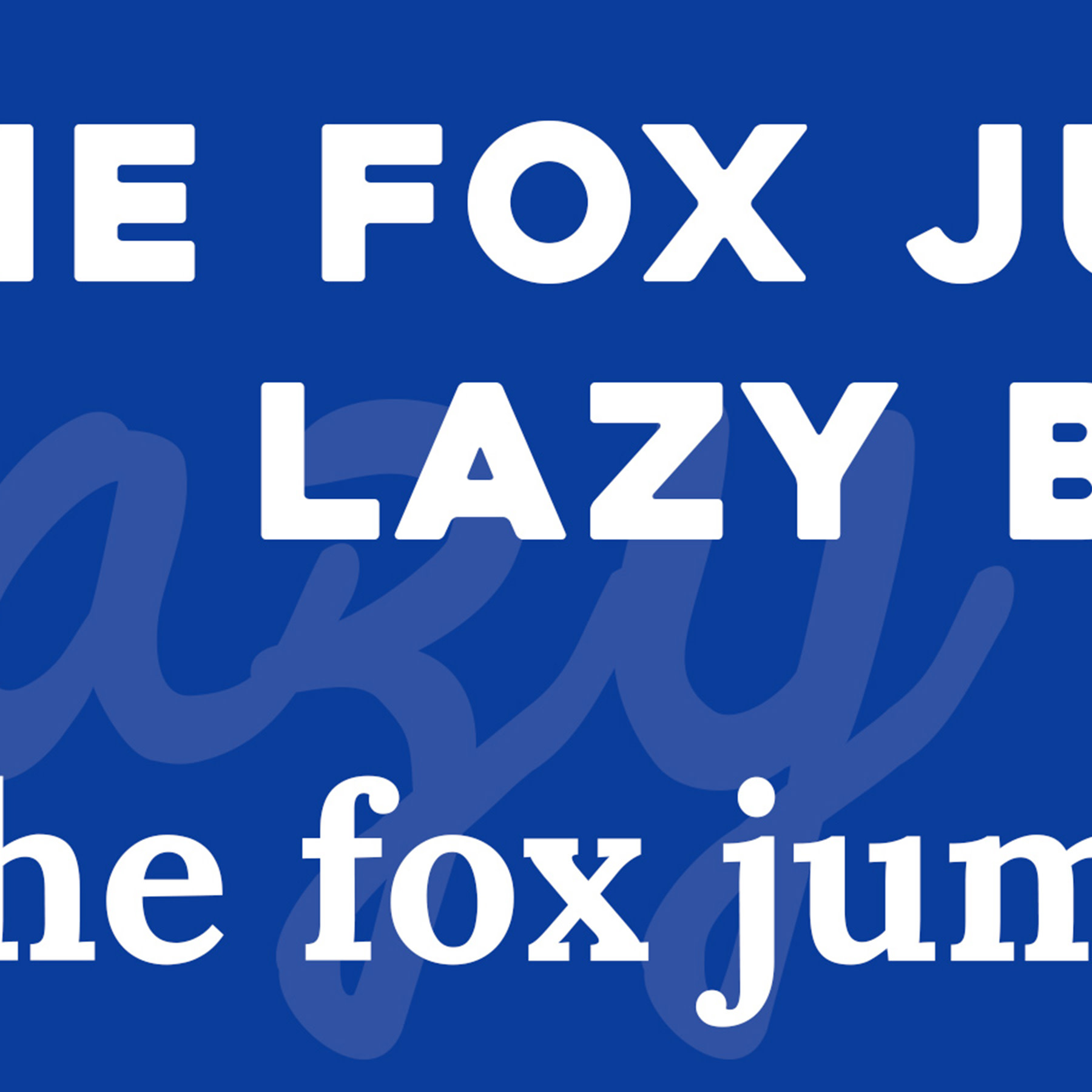
Het juiste lettertype kiezen voor je logo en huisstijl is belangrijk. Het draagt namelijk enorm bij aan de look & feel van je bedrijf. Welke indruk wil je in de eerste oogopslag maken? Moet het groots en uitbundig zijn? Of is het juist een bescheiden boodschap, verpakt in een fijne letterstijl? Veel bedrijven leggen de lettertypes die ze gebruiken vast in een huisstijlhandboek en voeren op die manier één lijn door in de Fonts op briefpapier, visitekaartjes, brochures, flyers, postermateriaal en ander drukwerk.
Binnen een zakelijke huisstijl wordt vaak één lettertype gehanteerd, maar wel meerdere Fonts. Dat komt omdat een lettertype - zoals de naam al zegt - alleen het lettersoort beschrijft, oftewel het type. Een Font is gedetailleerder. Veel mensen denken dat Font en lettertype hetzelfde is, ze worden vaak door elkaar gehaald. We hebben de verschillen voor je op een rij gezet.
Een lettertype is een set letters dezelfde stijl. Spreken we over een lettertype, dan hebben we het over het ontwerp van de letters. Bekende lettertypes zijn: Arial, Comic Sans, Times New Roman en Roboto. Een lettertype zegt niets over de grootte van de letters of over de stijl (dikgedrukt of cursief bijvoorbeeld).
Een Font geeft een complete beschrijving van de letters. In de ontwerpfase wordt door een vormgever vaak één of meerdere Fonts gemaakt, die in de gehele huisstijl van het bedrijf worden doorgevoerd. Een Font vertelt de gebruiker wat het lettertype is, welke stijl wordt gehanteerd (regular, cursief, onderstreept of bold) en wat je lettergrootte is. Een tekst in exact hetzelfde lettertype, maar in een andere stijl of grootte is een ander Font.
Een eigen Font maken doe je bij voorkeur met een grafisch programma als Adobe Illustrator. Photoshop is ook een optie, maar dit programma is meer gericht op het bewerken van foto’s. Om in Photoshop een Font te maken, zul je er eerst online een Font moeten downloaden en deze vervolgens openen en bewerken. Online zijn ook zogenaamde Font Generators te vinden. Deze bieden vaak wel minder mogelijkheden in het creëren van een unieke huisstijl. Vormgevers leggen Fonts vaak vast in een guideline. Hierbij wordt er voor elke uiting het lettertype, de -grootte, -stijl en -kleur benoemd. Op die manier wordt één lijn doorgevoerd in al het drukwerk.
Misschien heb je wel eens van WhatTheFont of Font Flipper gehoord? Dit zijn zogenaamde Font Finders, een soort Google voor Fonts. Heb je ergens een unieke letterstijl gespot en wil je weten welk Font het is? Dan kun je een foto of screenshot van deze letters uploaden om erachter te komen wat de specificaties zijn. Erg handig voor wie zich graag online laat inspireren!